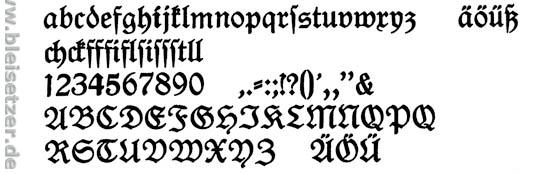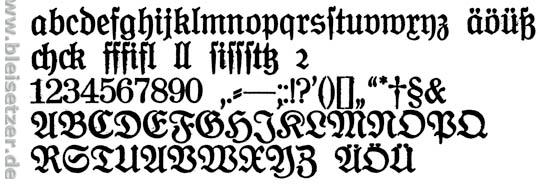
eher etwas für die Schrifthistoriker: seit wann gibt es denn das u und das j (in Minuskelform/in Versalform)? Die CAPITALIS MONUMENTALIS kannte weder das eine noch das andere. In ihrer quadratischen Variante bilde ich mir ein schon einmal ein u entdeckt zu haben? Mich interessiert einfach: mit welcher Schrift gab es denn offiziell U,u/J,j und wann ungefähr war das?
... oh, und wann das Endungs-s kam wäre ebenfalls gar interessant?!
Hier eine Rediviva von 1905 (eine Schwabacher) und eine Ideal-Fraktur von 1909. Das sind nur zwei von einer ganzen Reihe Beispiel Gebrochener Schriften, bei denen das I und das J identisch genutzt wurden. (Bei uns im Bleisatz spricht man allerdings nicht davon, daß das kein J gäbe).